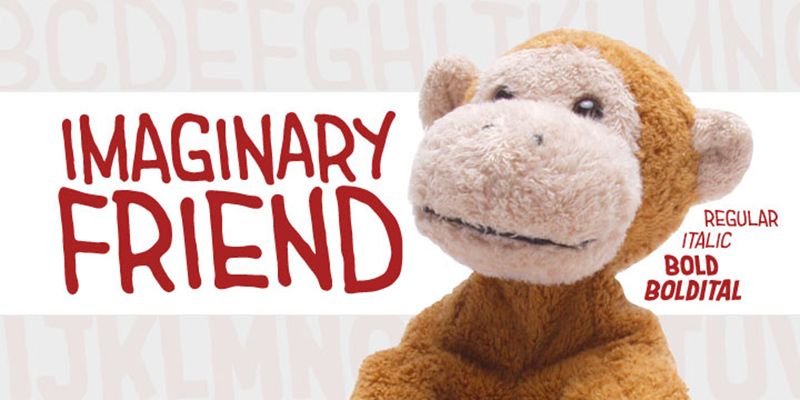
Blambot es la empresa del diseñador de tipografías Nate Piekos y está especializada en confeccionar estilos de fuentes para usarlos en la tipografía de cómics en papel y digitales. Blambot ha prestado servicios de diseño de fuentes y rotulaciones a casi todos las principales editoriales, como Marvel Comics, DC Comics, Dark Horse Comics, Image Comics, Oni Press y muchas otras. Las creaciones de Blambot disponen de licencias para videojuegos, películas, publicidad y paquetes de productos concedidas por empresas como Microsoft, Six Flags Amusement Parks, Charles Schulz & Associates, New Yorker Magazine, The Gap, Penguin Random House y Sony.